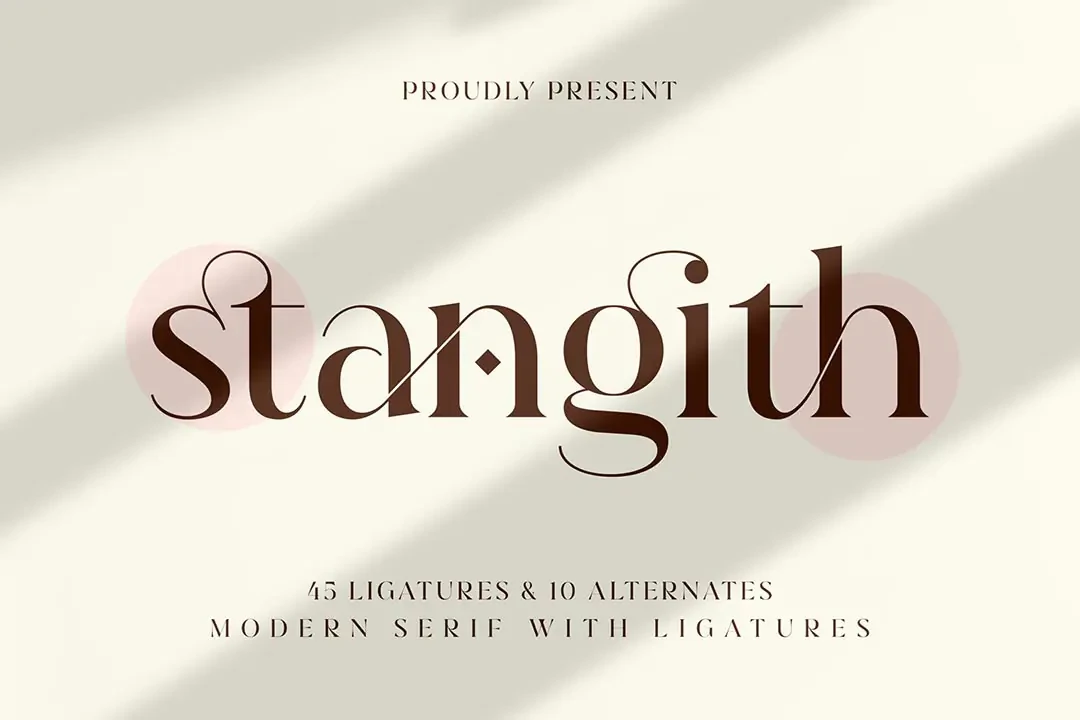
Stangith Yazı Tipi
Merhaba. Tanıtıyoruz, Stangith – Ligatures modern Serif, harfleri akıcı biçimde bağlayan ligatürler kullanan zarif ve benzersiz bir yazı tipidir. Sözcük işaretli logolar, monogramlar veya alıntılar için benzersiz bir dokunuş eklemek için idealdir. Stangith 45 ligatür ve 10 Alternatif ile ayrıca
Merhaba. Tanıtıyoruz, Stangith – Ligatures modern Serif, harfleri akıcı bir şekilde bağlamak için ligatürler kullanan zarif ve benzersiz bir yazı tipidir. Sözcük işaretli logolar, monogramlar veya alıntılar için benzersiz bir dokunuş katmak için mükemmeldir. Stangith 45 ligatür ve 10 Alternatif ile sayılar ve noktalama işaretlerini de içerir; bu onu süper harika yapar. Gerekirse ligatür kapatılabilir; standart yazım için gereklidir. Herhangi bir sorunuz mu var? Sadece sorun!